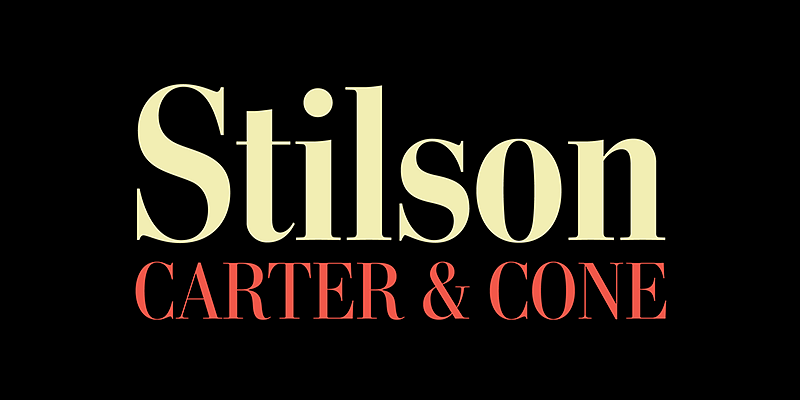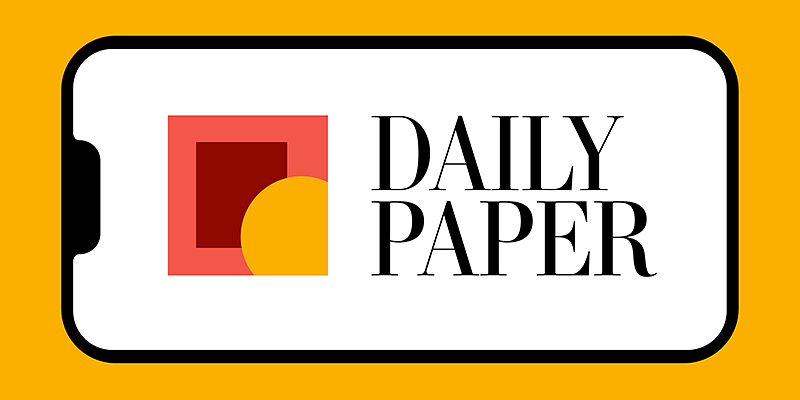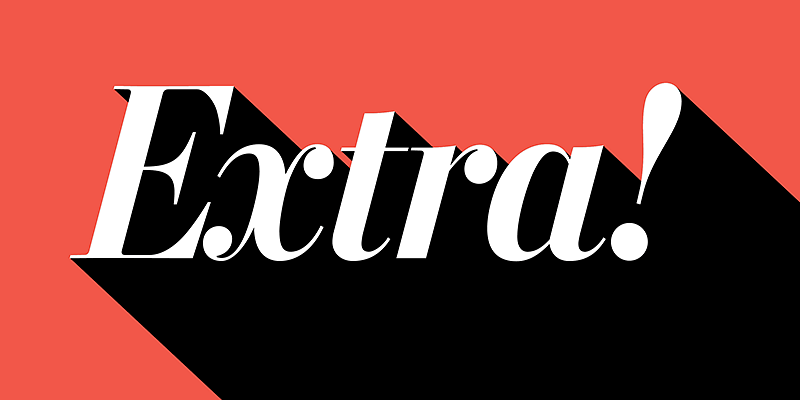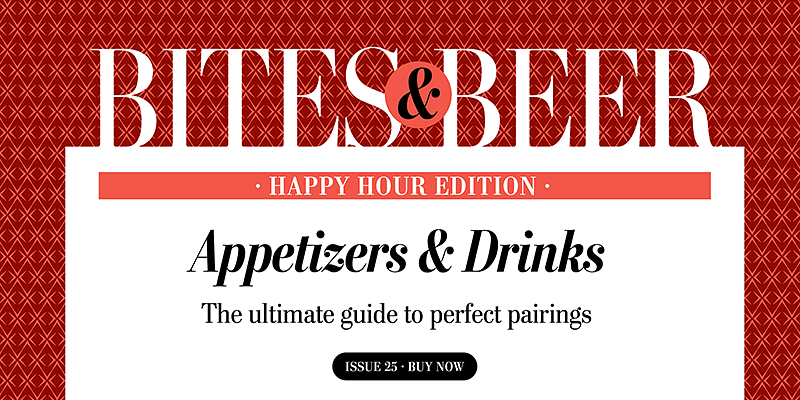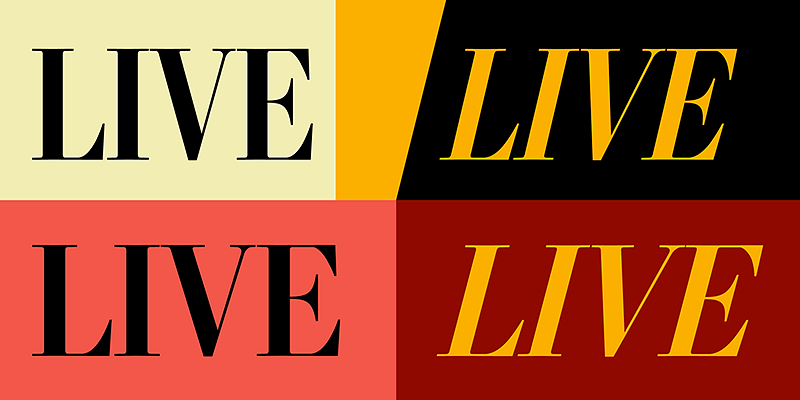
Carter & Cone ha progettato alcuni dei font più celebri al mondo e font personalizzati pluripremiati. Eleganti, equilibrati, utili: queste parole descrivono i font prodotti dalla collaborazione di Matthew Carter e Cherie Cone. Sebbene i loro primi lavori costituiscano il fondamento della composizione tipografica moderna, i loro font più recenti continuano ad arricchirla ed espanderla. La coerenza e la completezza dei loro design sono il risultato diretto della loro prima formazione in settori senza possibilità di annullamento, come la fustellatura e la calligrafia.